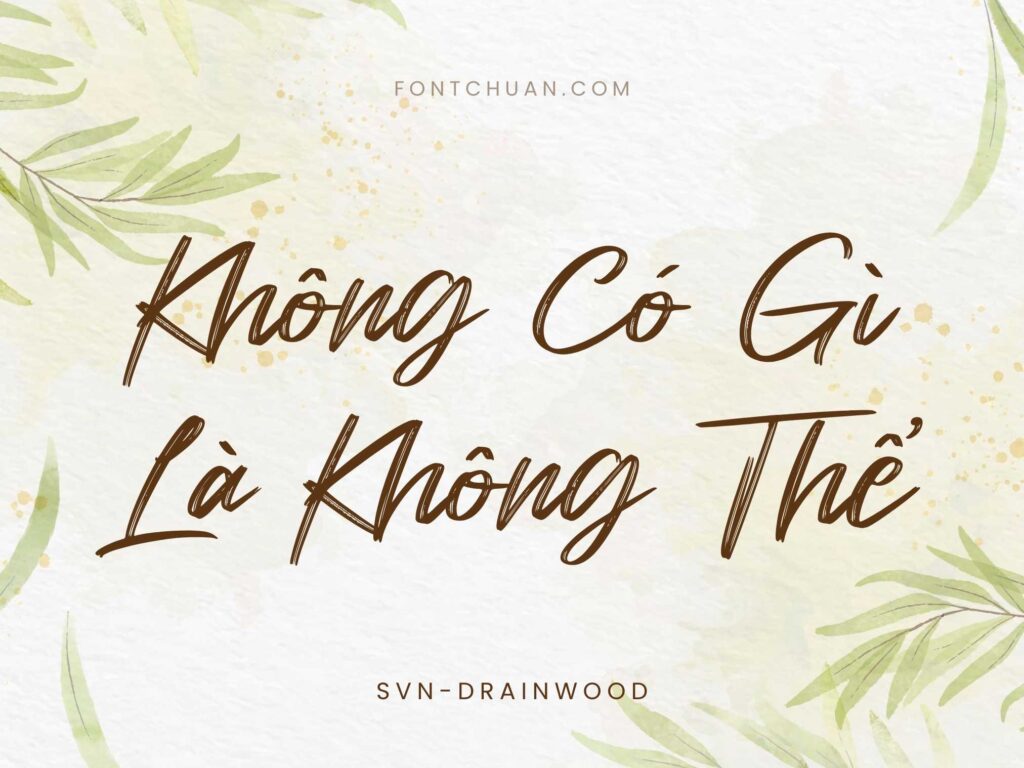
Font SVN Drainwood Việt Hóa
Tác giả Font: Muhammad Sirojuddin
Drainwood là một font chữ script với nét cọ tự nhiên, được thiết kế bởi Fontherapy. Font này mang lại cảm giác mạnh mẽ, thanh lịch và năng động, phù hợp cho các dự án thiết kế như tiêu đề, logo, thiệp mời, áo thun, trích dẫn và nhiều ứng dụng sáng tạo khác. Với các đường nét uyển chuyển và giàu tính nghệ thuật, Drainwood cũng có thể được sử dụng như một Font cổ trang hoặc Font chữ thư pháp, giúp các thiết kế mang phong cách hoài cổ, trang trọng và cá nhân hóa hơn. Font đã được Việt hóa để hỗ trợ tiếng Việt bởi STYLEno.1 Fonts, đồng thời hỗ trợ nhiều ngôn ngữ khác, giúp mở rộng phạm vi sử dụng trên toàn cầu. Font này được chia sẻ miễn phí cho mục đích sử dụng cá nhân; để sử dụng cho mục đích thương mại, bạn nên mua bản quyền từ nhà phát hành.
Đặc điểm thiết kế của Drainwood bao gồm các nét chữ viết tay mềm mại và thanh lịch, tạo cảm giác thân thiện và gần gũi. Font này phù hợp cho các ứng dụng như tiêu đề, logo, thiệp mời, áo thun, trích dẫn và nhiều dự án sáng tạo khác. Các ngành nghề phù hợp bao gồm quảng cáo, nghệ thuật và thiết kế đồ họa.